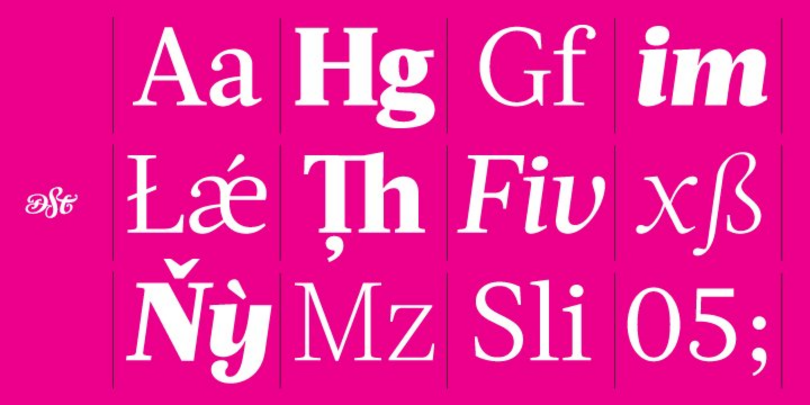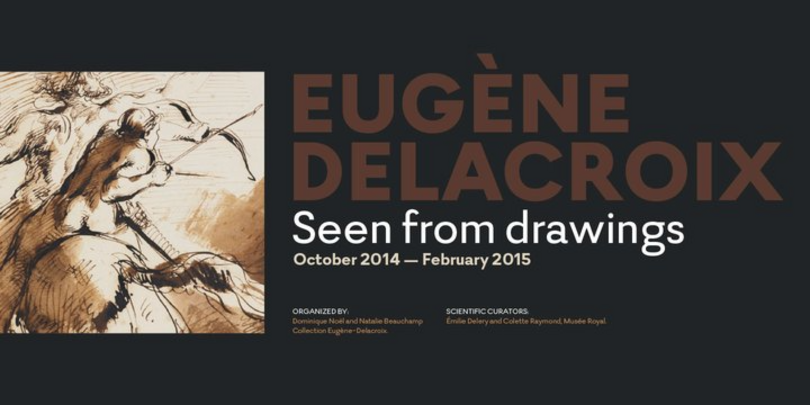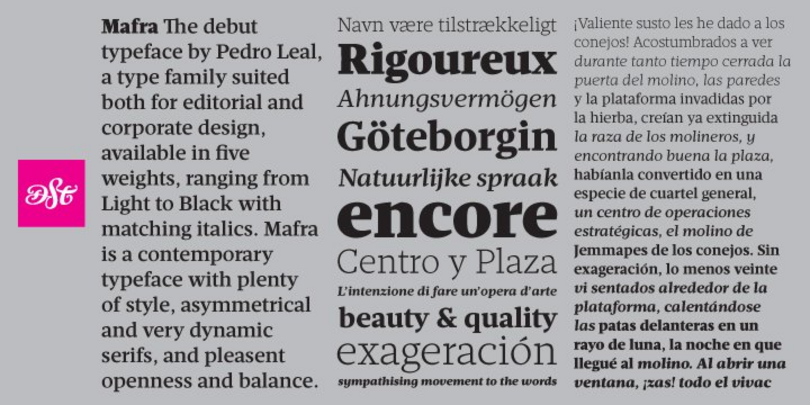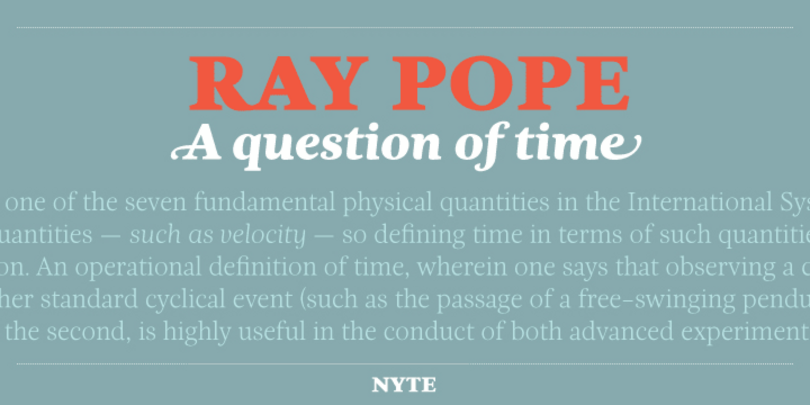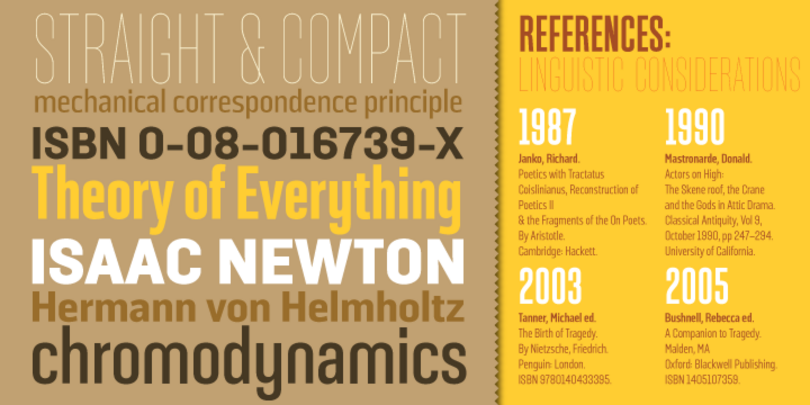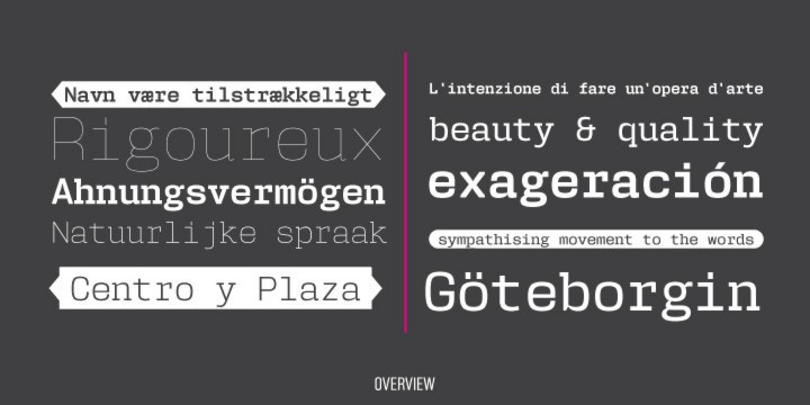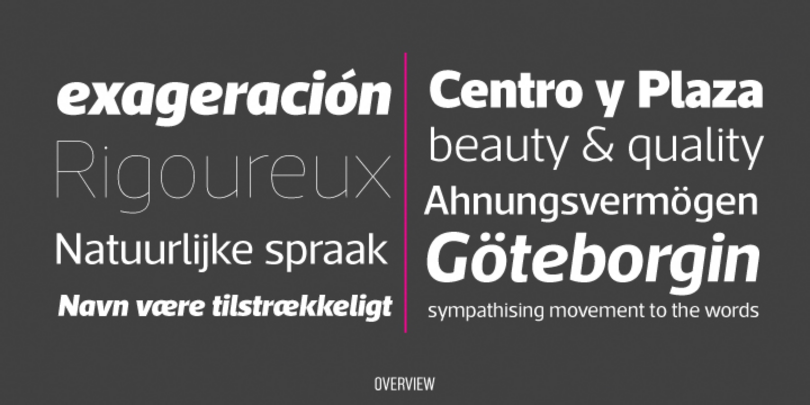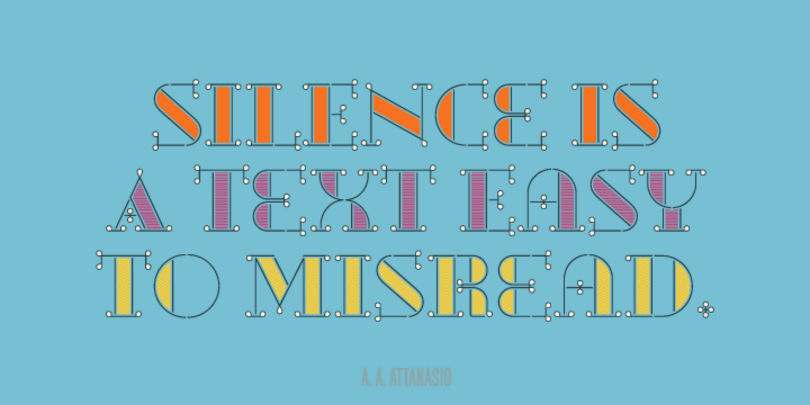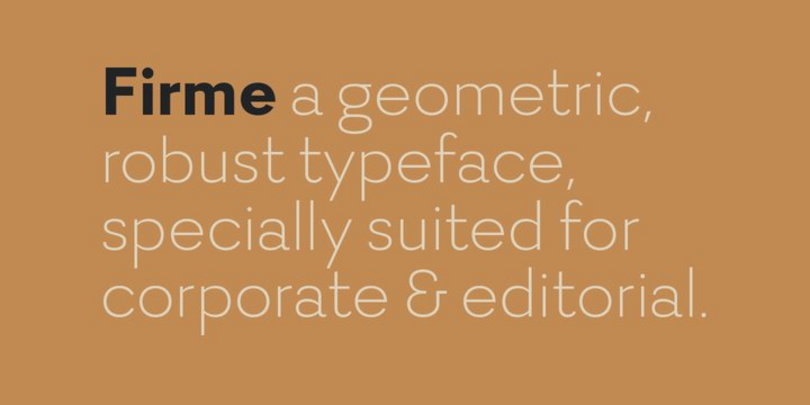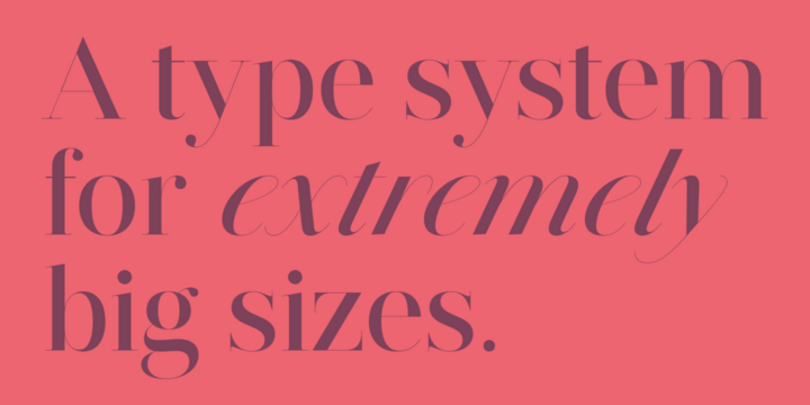
DSType.
Basée à Porto, au Portugal, DSType est une fonderie de caractères indépendante, fondée en 1994 par Dino dos Santos. Cette fonderie primée est spécialisée dans la conception de caractères pour les magazines, les journaux, les entreprises et les institutions culturelles. Axées sur les projets éditoriaux, les polices de DSType ont été utilisées dans de nombreuses publications de renom, telles que Forbes et le New York Times Magazine. DSType a travaillé avec des marques, des événements et des agences de renommée internationale pour créer des identités d'entreprise, des campagnes de marketing et des caractères personnalisés, notamment Banco CTT, FIFA World Cup Qatar 2022, Electronic Arts, ESPN, Gatorade, McCann-Erickson, Starbucks, et bien d'autres encore. Dino dos Santos est reconnu comme un pionnier de la typographie portugaise, et a publié le premier livre du pays sur la calligraphie portugaise.
Solido
Solido est un système typographique très polyvalent et disponible en cinq largeurs : Solido, Solido Constricted, Solido Condensed, Solido Compressed et Solido Compact, pour un total de 35 polices qui comptent de nombreux caractères alternatifs.
Acta
Conçue pour le journal chilien La Tercera en 2010, Acta est une famille de polices épurée et rafraîchissante, suffisamment conservatrice pour être utilisée dans un journal. Le système complet Acta Type comprend Acta et Acta Display, toutes deux dotées de six graisses et de l’italique correspondant. Acta Symbols offre une collection étonnante de symboles spécialement conçus pour les journaux et les magazines, tandis que la version avec graisse Heavy, Acta Poster, est élégante et accrocheuse avec ses trois styles aux nombreuses ligatures et variantes.
Nyte
Nyte a été créée à l’origine lors de la refonte du The New York Times Magazine. Étroitement inspirée de l’ancienne police de caractères de la fonderie Esta, Nyte a été introduite pour un public plus large dans un jeu de polices et de caractéristiques OpenType qui permettent au texte de se démarquer lorsqu’il est utilisé dans les titres et les petits passages de texte, tout en offrant une grande lisibilité et une utilisation optimale de l’espace lorsqu’elle est utilisée dans les corps de texte.
Acto
Acto est un système typographique conçu comme la version sans serif de la famille de polices Acta de DSType. Les deux familles de polices ont été créées en 2010 à l’occasion de la refonte du journal chilien La Tercera, mais contrairement à certaines des polices précédentes de la fonderie (par exemple, Leitura), Acto ne correspond pas exactement à Acta en termes de structure, et peut donc être utilisée de manière autonome. Les capitales ayant la même hauteur que les ascendants, la fonderie a créé un « l » incurvé afin d’éviter toute confusion potentielle avec le « I ». Ce thème a été continuellement appliqué en supprimant les éperons du b et du g pour donner ainsi un aspect chaleureux à la police. Au final, Acto est une famille de polices sans très puissante, qui offre onze graisses avec des italiques assortis, parfaite pour la conception éditoriale et d’entreprise.
User
User est une famille de polices à chasse fixe qui compte 30 styles, de Hairline à Bold, divisés en Regular, Upright et Stencil, avec cinq graisses (Hairline, ExtraLight, Light, Medium et Bold), et toutes avec des versions Cameo. Complexité et polyvalence sont les maîtres mots de cette famille de polices. Bien qu’il s’agisse d’une police à chasse fixe (sans crénage), tous les glyphes ont été conçus pour s’adapter facilement à la largeur de 600 points, une tâche difficile car certains glyphes sont trop étroits (« i » et « l »), tandis que d’autres sont trop larges (« m » et « w »), mais ils doivent tous s’adapter à la même largeur. Le désir de garantir une lisibilité confortable était une considération clé, plusieurs ligatures ont été conçues pour s’adapter à la largeur d’espace simple et double, permettant au designer de conserver une aura à la conception proportionnelle.
Jules
À première vue, Jules semble n’être qu’une variation de plus de la police Didonic, mais en y regardant de plus près, cette police commence à dévoiler toutes ses caractéristiques extraordinaires, alors qu’elle est spécialement conçue pour être utilisée dans des tailles extrêmement grandes. Jules reflète la fin du XVIIIe siècle et s’inspire de plusieurs planches d’un calligraphe portugais nommé Antonio Jacintho de Araujo. Elle est disponible dans trois tailles optiques différentes : Big, Colossal et Epic, Jules dispose de nombreuses ligatures et d’alternatives stylistiques, ainsi que d’italiques raffinés et d’une version très élégante avec ornements.
Braga
Braga est une police de caractères baroque et exubérante nommée d’après une ville portugaise qui est également connue comme la capitale baroque du Portugal. Cette extravagance typographique s’accompagne d’une multitude de polices conçues pour fonctionner comme des calques, permettant au designer d’insérer de la couleur, des lignes, des dégradés, des motifs, du baroque, des ornements floraux et bien d’autres éléments graphiques. En commençant par Braga Base, n’importe lequel des vingt-trois styles disponibles peut être ajouté pour créer des designs typographiques colorés.
Aparo
La famille de polices Aparo est un mélange unique de typographie et de calligraphie, de versions liées et non liées. Aparo combine le meilleur de ces deux univers dans une police de caractères simple mais complexe. En apparence, Aparo est un caractère romain gras et italique très simple, mais il possède de nombreuses caractéristiques calligraphiques, notamment des barres obliques qui font ressortir les mots, des détecteurs de collision pour éviter les combinaisons étranges, des caractères alternatifs activés par défaut pour améliorer l’effet calligraphique et un ensemble de caractères très étendu de 897 glyphes au total.
Firme
Firme est la version personnelle du designer concernant les polices géométriques. Cette police robuste est particulièrement adaptée aux projets d’entreprise et éditoriaux, offrant plusieurs alternatives stylistiques et des ligatures discrétionnaires pour une meilleure flexibilité typographique.
Mafra
Mafra est une police de caractères avec beaucoup de style, des empattements asymétriques et très dynamiques, ainsi qu’une ouverture et un équilibre agréables. La famille de polices est adaptée à la fois à la conception éditoriale et d’entreprise, et elle est disponible en cinq graisses, allant de Light à Black, avec les italiques correspondants.